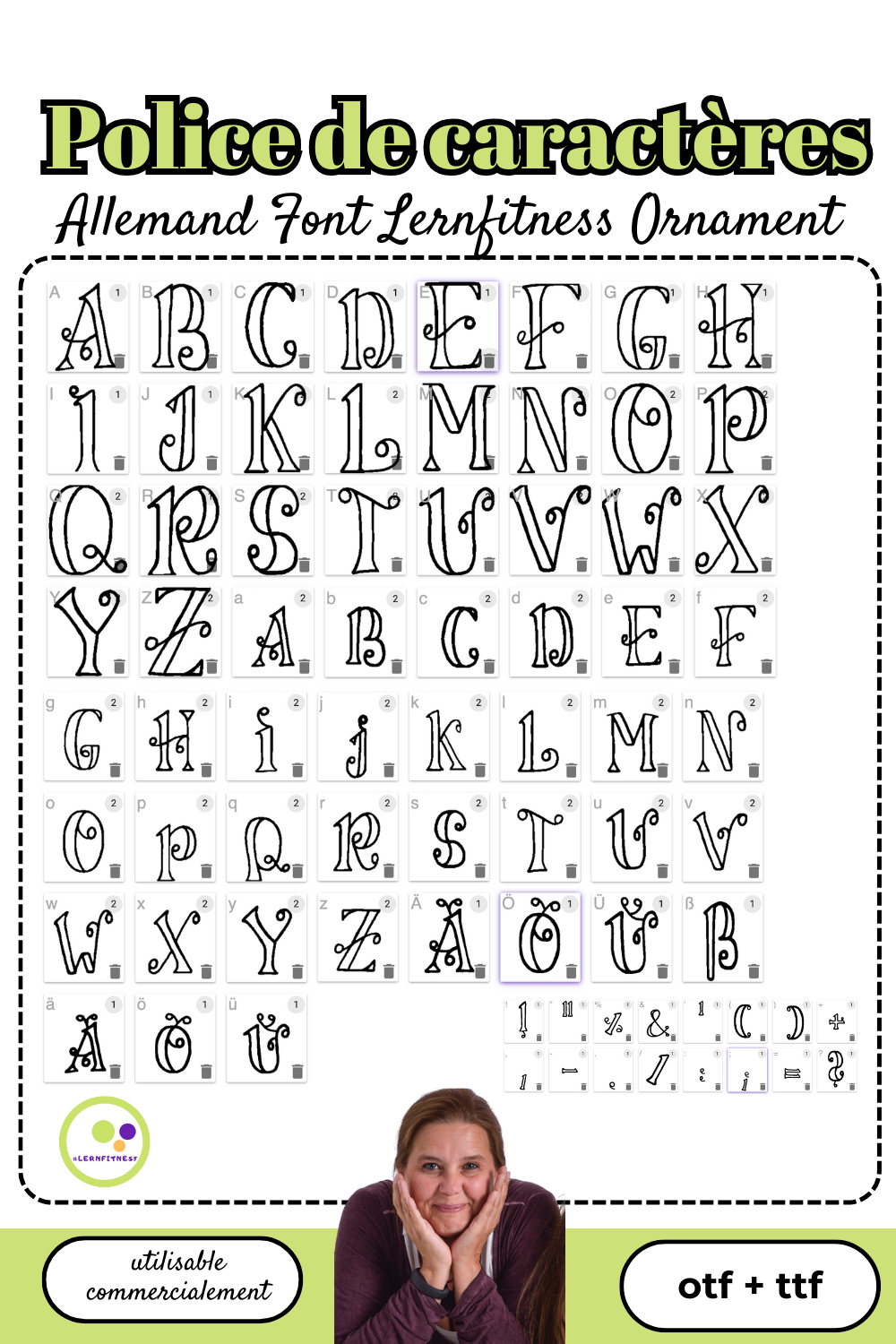
Font Lernfitness Ornament | police de caractères allemande + anglais | commerciale | police décorative
Cette police a été dessinée avec amour par mes soins.
Elle est composée de toutes les lettres courantes en Allemagne, y compris les trémas ä, ö, ü.
Font | police de caractères allemande + anglais | décorative